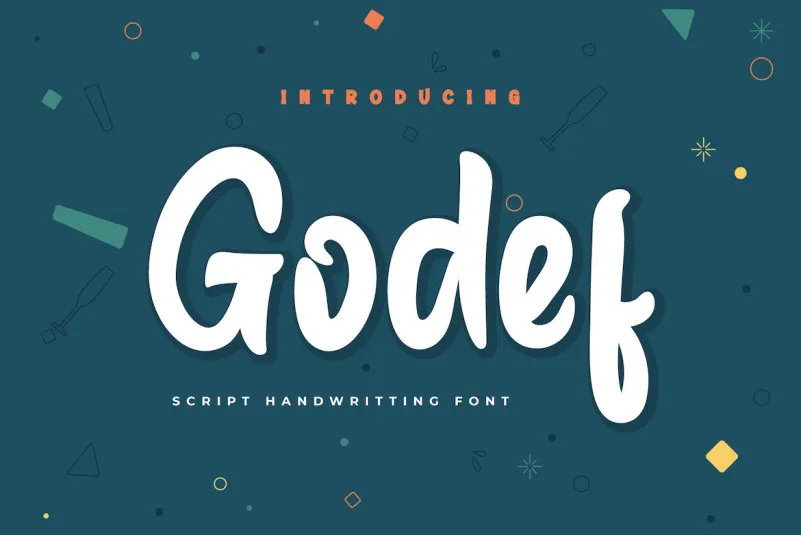
Godef Font – Download Grátis
Esta é uma fonte criada usando uma delicada e encantadora mão do designer, resultando num estilo elegante e bonito que se destaca perfeitamente para textos e cabeçalhos de projetos especiais. A Godef Font oferece um toque personalizado com sua forma arredondada e detalhes sutis, ideal tanto para criações digitais quanto impressas. Seja você designer ou ilustrador, essa fonte permite que suas ideias sejam transmitidas de maneira única e sofisticada, tornando-a perfeita para trabalhos de design que exigem uma elegância especial. Com seu acabamento cuidadosamente detalhado, a Godef Font é um excelente recurso para quem deseja adicionar um toque único às suas criações digitais ou impressas.